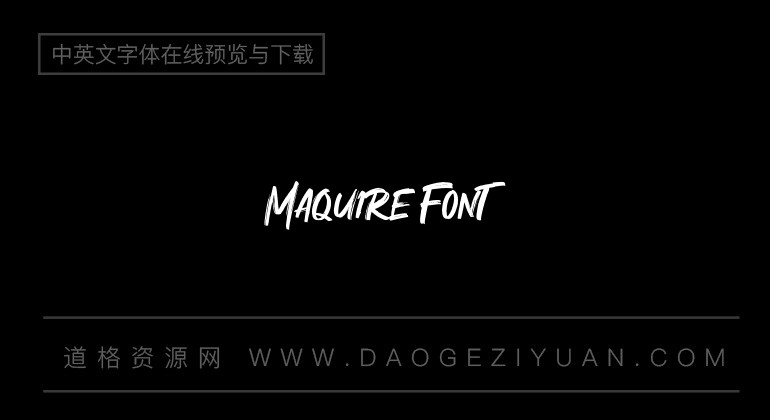
Maguire Font 是一种现代的手写风格字体,由设计师 Philip Trautmann 创造。它拥有流畅的曲线和独特的笔画,适合用于标题、标语、海报、包装设计等多种设计应用。 Maguire Font 具有多种字母、数字和标点符号,可用于多种语言。它提供了两种字重:Regular 和 Bold,每种字重都有一个斜体版本。这使得设计师可以根据需要选择不同的字重和斜体,以增强视觉效果。 Maguire Font 的设计灵感来自手写字体和印刷字体,它的设计旨在提供一种自然、舒适的阅读体验。因此,它适用于许多设计领域,包括品牌设计、视觉传达、广告等。内容介绍
Maquire Font是一款非常不错的手写艺术字体,具有很好的视觉感,适合于文化类的宣传设计、商业类品牌的广告和产品包装设计以及个性化文字排版等较多场景。